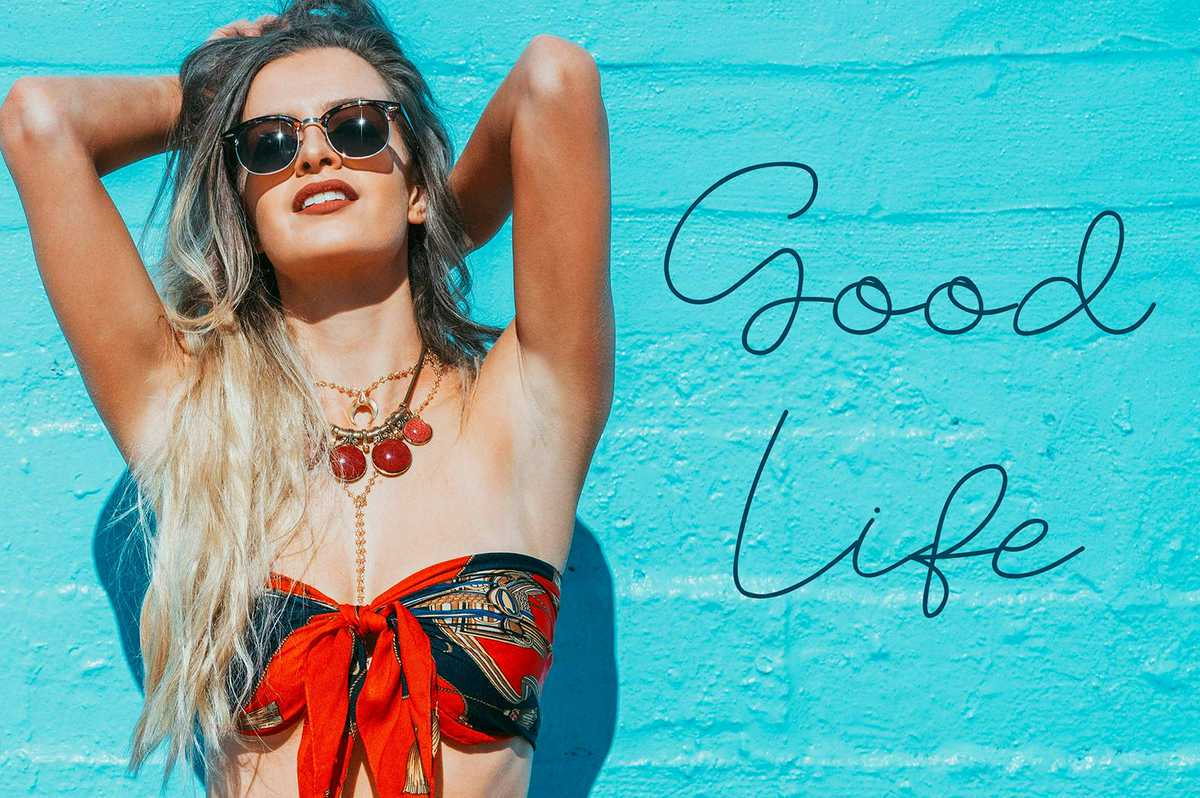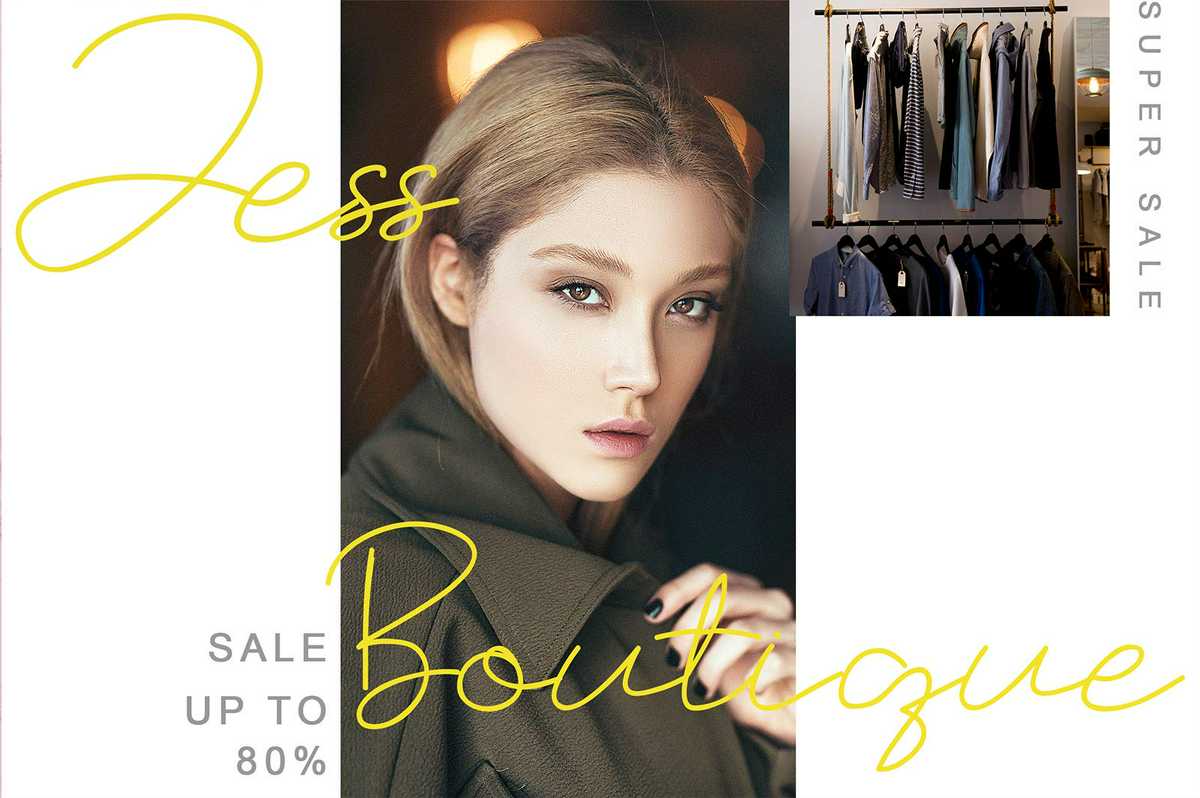
TheRusslandisModern&freshscript。它是一种风格独特的手写体风格,使其成为AnaturalandClassyLook。它可以形成各种不同的项目,如徽标和品牌、邀请函、文具、婚礼设计、社交媒体、广告、产品包装、产品设计、标签、摄影、水印、特价品等!TheRusslandisModern&freshscript。它是一种风格独特的手写体风格,使其成为AnaturalandClassyLook。它可以形成各种不同的项目,如徽标和品牌、邀请函、文具、婚礼设计、社交媒体、广告、产品包装、产品设计、标签、摄影、水印、特价品等!